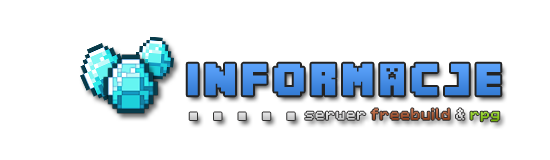
Czcionka minecraft
ja udostępniłem kiedyś czcionkę polską minecraft:
A co do tej z creeperem:
Zabawa opcjami mieszania warstwy.
Tworzysz tekst, następnie w opcjach warstwy wybierasz opcje mieszania.
Gradient, obrys na 1 piksel oraz cień.
Obrys na 1 piksel, nałożenie bialego koloru i blask zewnętrzny.
Gradient
Obrys